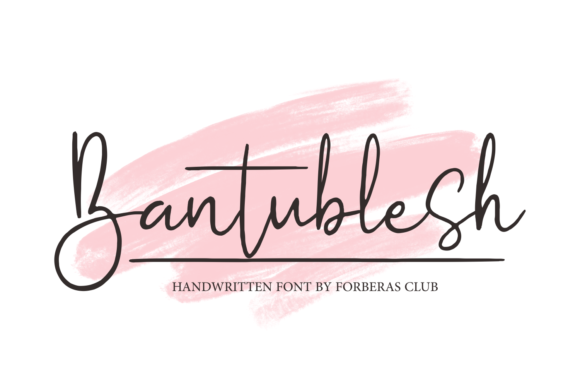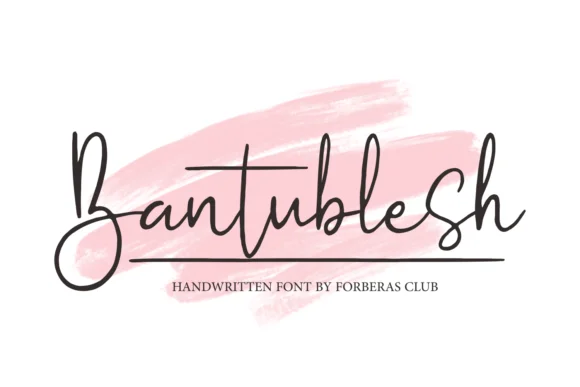
Название: Bantublesh Font (2021)
Bantublesh - это причудливый и элегантный рукописный шрифт, созданный для того, чтобы поразить вашу аудиторию и заставить ваш брендинг сиять.
Заставьте ваши проекты танцевать с этим замечательным шрифтом, где бы вы его ни использовали. Он идеально подходит для заголовков, логотипов, рекламы, печатных цитат, упаковки и даже для брендинга вашего сайта или социальных сетей.
Каждая буква имеет уникальный и красивый оттенок, который оживит ваш дизайн!